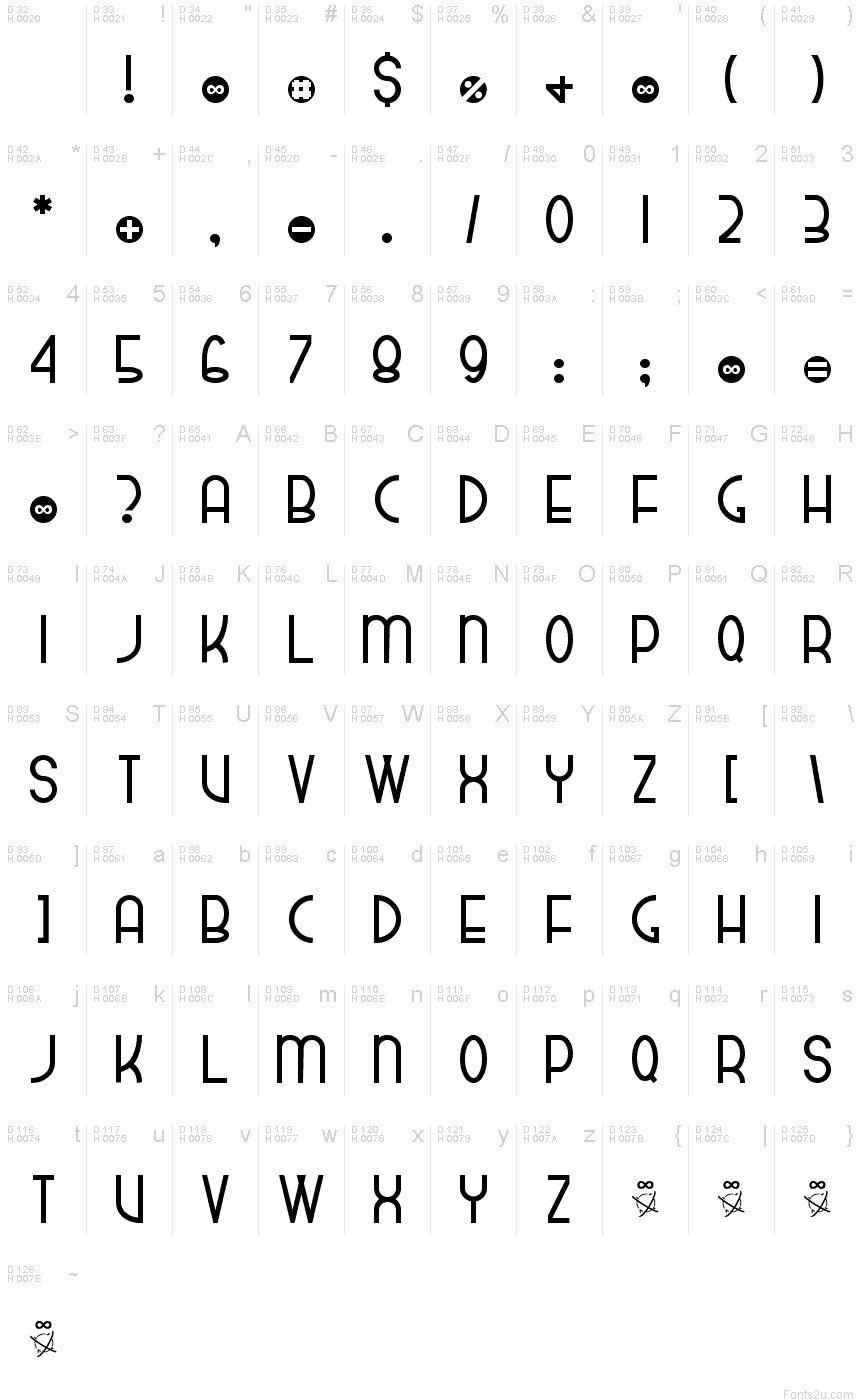
Krój pisma Dekthusian to darmowy, retro font typu display o eleganckiej, wyprostowanej postawie i wyrazistych, nasyconych liniach. Litery sprawiają wrażenie zaprojektowanych z precyzją, a jednocześnie eleganckich – proste pionowe kreski, czyste łączenia i charakterystyczna, zakrzywiona nóżka litery K nadają całości subtelne napięcie w stylu Art Deco. W efekcie otrzymujemy znaki, które pasują do dawnych witryn sklepowych, okładek płyt i starych szyldów kinowych, a mimo to wyglądają wystarczająco nowocześnie, by sprawdzić się w dzisiejszym brandingu.
Nagłówki złożone fontem Dekthusian zyskują solidny rytm, który łatwo się czyta. Ten darmowy krój doskonale sprawdzi się na plakatach, okładkach albumów, w logotypach, na opakowaniach, w tytułach redakcyjnych i w oprawie wydarzeń – wszędzie tam, gdzie chcesz dodać silny, lekko nostalgiczny akcent. Spróbuj połączyć Dekthusian w nagłówkach z prostym bezszeryfowym krojem lub lekką antykwą w tekście głównym i pozwól mu wybrzmieć w dużym rozmiarze, aby wyeksponować te pewne, architektoniczne formy.